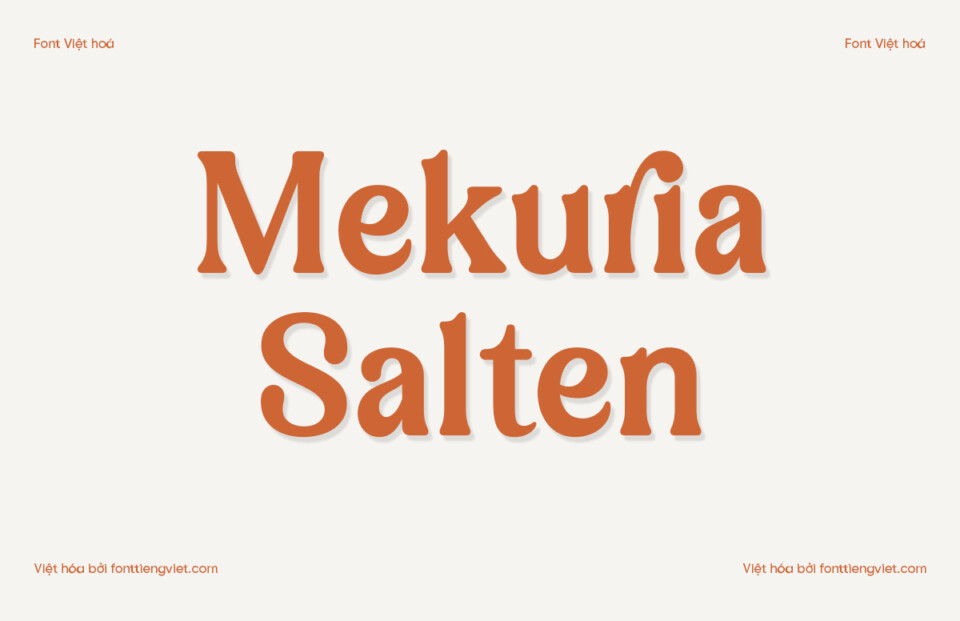
Font Việt hóa 1FTV VIP Mekuria Salten
Font Việt hóa 1FTV VIP Mekuria Salten – Đẳng cấp thiết kế hiện đại và tinh tế
Giới thiệu về Font Việt hóa 1FTV VIP Mekuria Salten
Trong thế giới đồ họa hiện đại, việc tìm kiếm một bộ Font Miễn Phí chất lượng cao và phù hợp với tiếng Việt luôn là ưu tiên hàng đầu của các nhà thiết kế. Font Việt hóa 1FTV VIP Mekuria Salten nổi lên như một giải pháp hoàn hảo, kết hợp giữa sự sang trọng cổ điển và nét phá cách đương đại. Bộ font này được đội ngũ 1FTV chăm chút kỹ lưỡng, đảm bảo mọi ký tự có dấu đều hiển thị mượt mà, không xảy ra lỗi font hay mất nét khi sử dụng trong các phần mềm thiết kế chuyên nghiệp. Với đường nét thanh mảnh nhưng chắc chắn, Mekuria Salten mang đến một cảm giác chuyên nghiệp, rất phù hợp cho những ai đang tìm kiếm sự khác biệt trong các dự án sáng tạo cá nhân cũng như thương mại.
Đặc điểm nổi bật của Font Việt hóa 1FTV VIP Mekuria Salten
Thiết kế độc đáo và tính ứng dụng cao
Điều làm nên sức hút của Font Việt hóa 1FTV VIP Mekuria Salten chính là cấu trúc hình học cân đối và các chi tiết uốn lượn tinh xảo. Font chữ này thuộc phong cách Serif hiện đại, tạo nên sự tin cậy nhưng vẫn giữ được nét mềm mại cần thiết. Bạn có thể dễ dàng sử dụng bộ font này cho nhiều mục đích khác giả nhau như thiết kế logo, bìa sách, poster sự kiện hay các ấn phẩm tạp chí thời trang. Sự linh hoạt của nó giúp người dùng dễ dàng truyền tải thông điệp một cách ấn tượng và lôi cuốn nhất.
Khả năng tương thích và tối ưu hóa tiếng Việt
Mekuria Salten phiên bản VIP từ 1FTV đã được tối ưu hóa hoàn toàn cho bảng mã Unicode. Điều này có nghĩa là các dấu thanh như huyền, sắc, hỏi, ngã, nặng được đặt ở vị trí chuẩn xác, giúp tổng thể văn bản trông tự nhiên và dễ đọc. Đối với các bạn học sinh hay thầy cô giáo, việc sử dụng Font Việt hóa 1FTV VIP Mekuria Salten để trình bày bài giảng điện tử hoặc làm các slide thuyết trình sẽ giúp nội dung trở nên trực quan và thu hút sự chú ý của người xem hiệu quả hơn hẳn các font chữ hệ thống thông thường.
Lợi ích khi sử dụng Font Việt hóa 1FTV VIP Mekuria Salten
Sử dụng một bộ font được việt hóa bài bản không chỉ giúp bạn tiết kiệm thời gian chỉnh sửa mà còn nâng tầm giá trị thẩm mỹ cho tác phẩm. Font Việt hóa 1FTV VIP Mekuria Salten cung cấp nhiều biến thể định dạng khác nhau, từ nét mảnh (light) đến nét đậm (bold), cho phép người dùng tự do sáng tạo và phân cấp nội dung rõ ràng. Việc sở hữu một bộ font “VIP” trong thư viện thiết kế sẽ giúp bạn tự tin hơn khi thực hiện các dự án yêu cầu độ tinh tế cao. Ngoài ra, tính thẩm mỹ của font còn hỗ trợ rất tốt trong việc xây dựng bộ nhận diện thương hiệu cá nhân bền vững.
Kết luận và hướng dẫn trải nghiệm